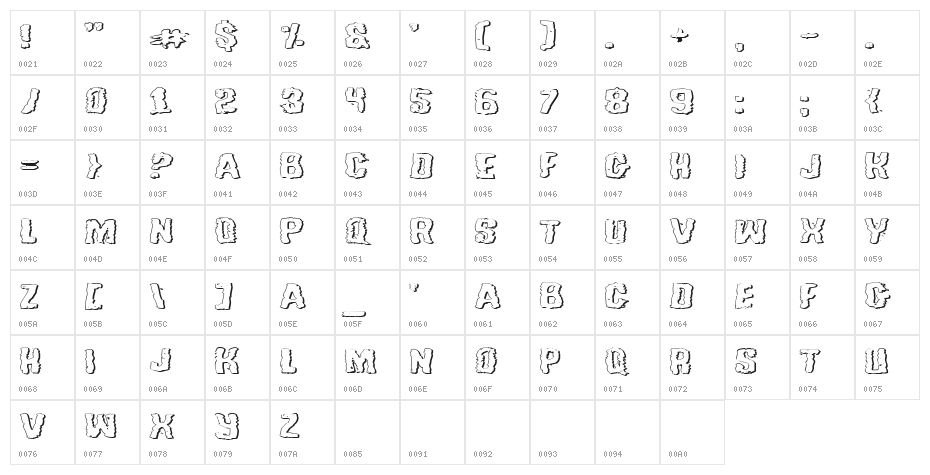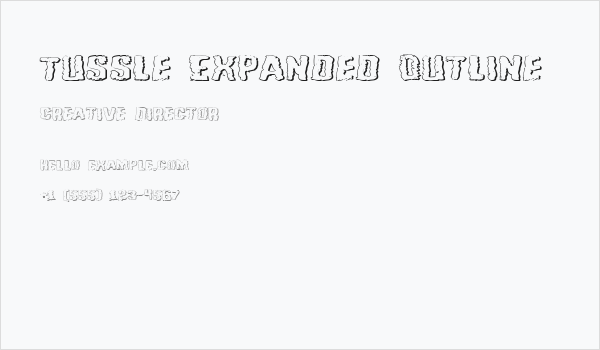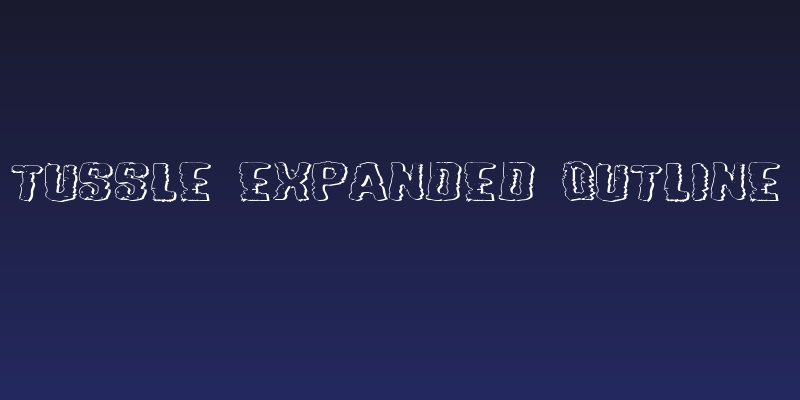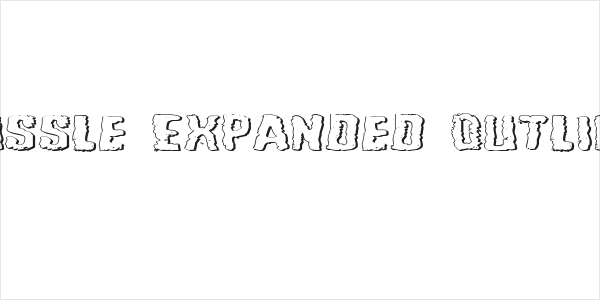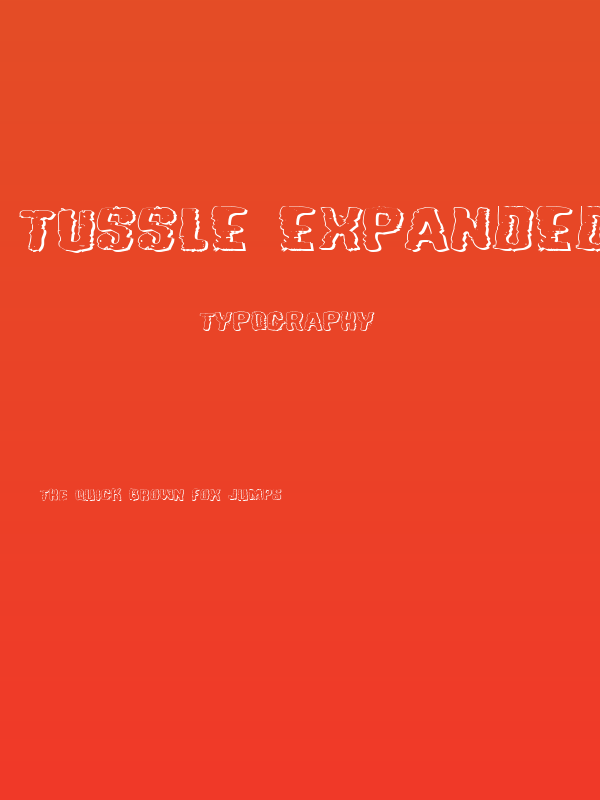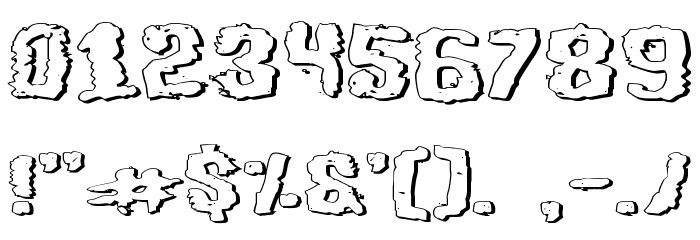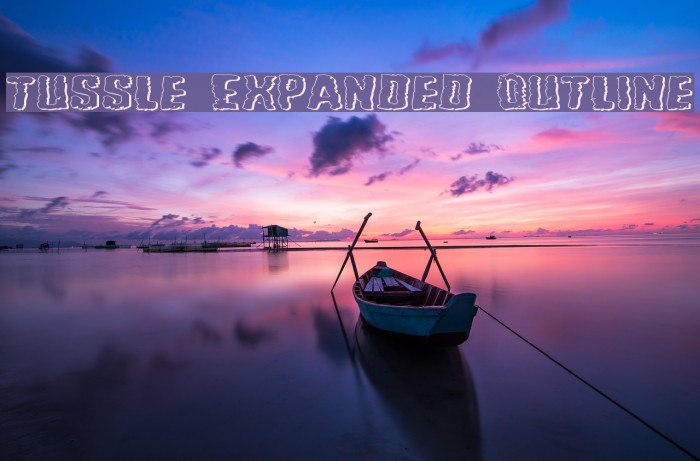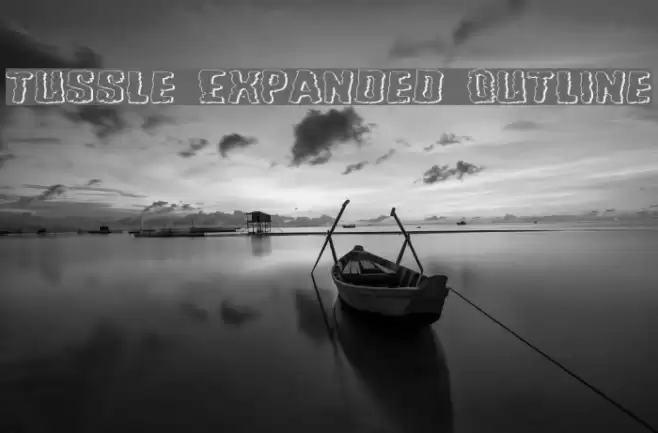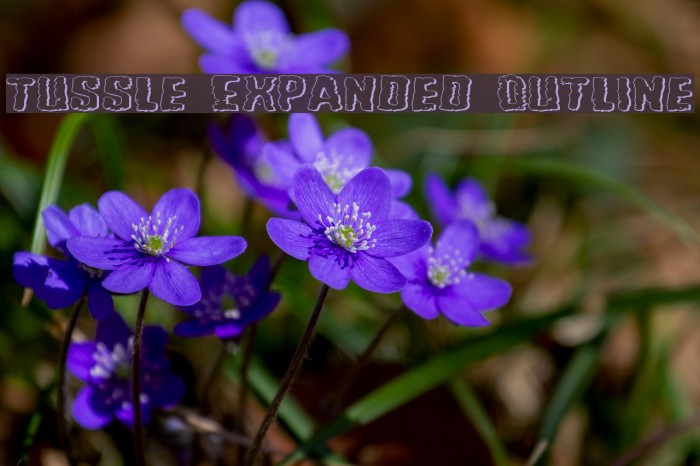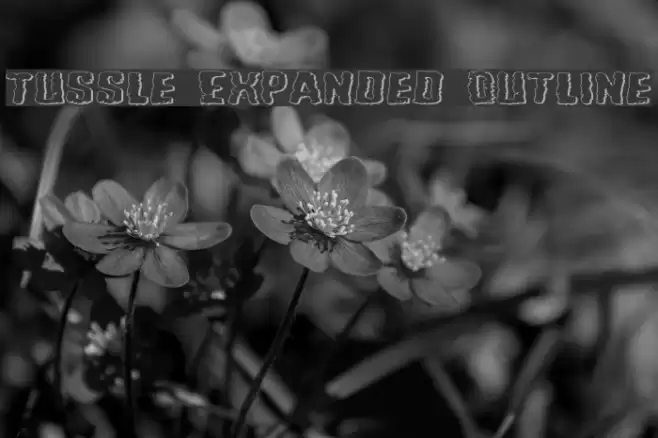
Tussle Expanded Outline Font
| おすすめプロジェクト | Ideal for poster designs, comic book titles, video game graphics, and any creative project needing a bold, dynamic typeface. |